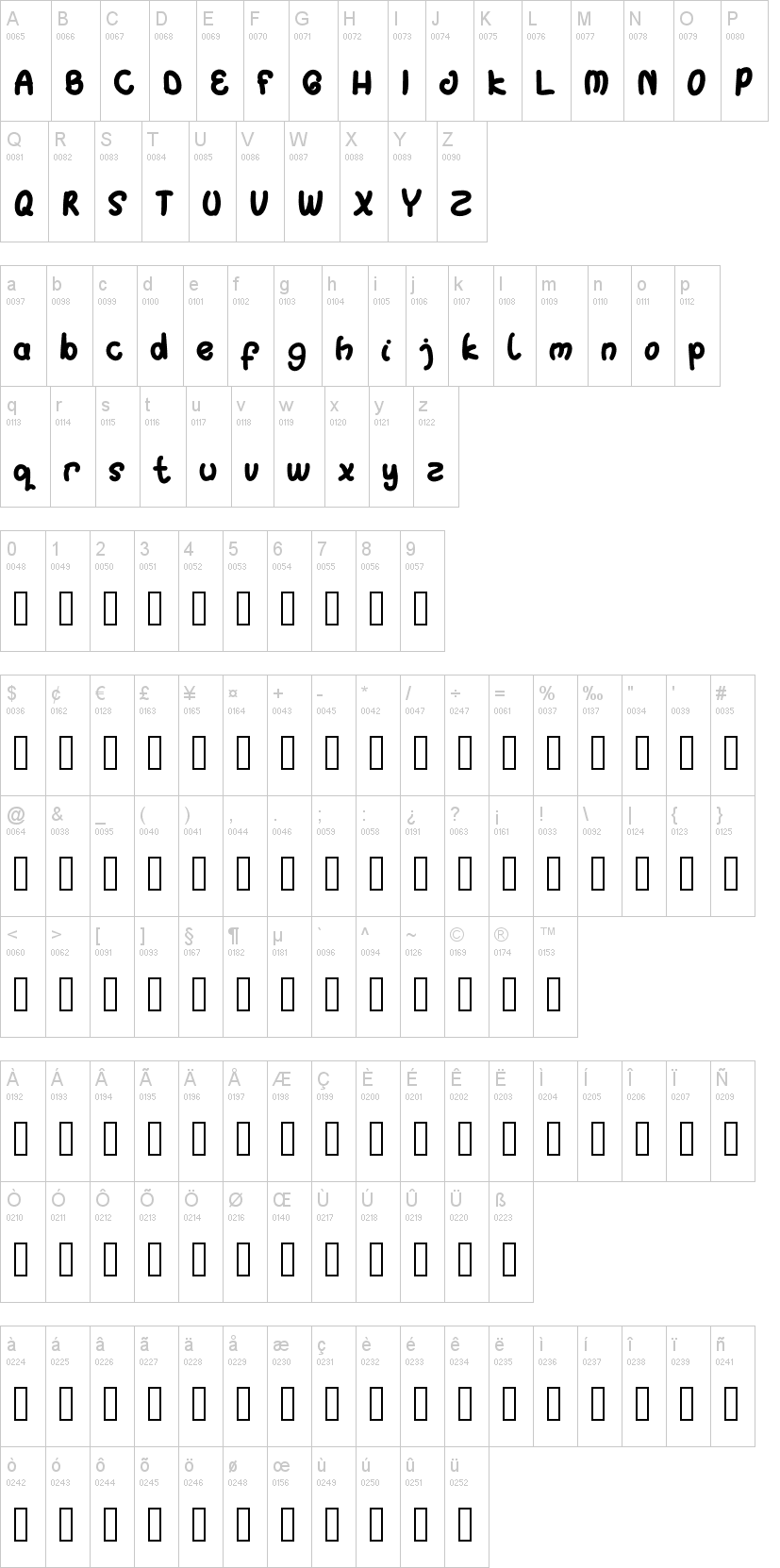
Singo
Singo 是一款非常流行的新型数字字体,它具有极具现代感的外观,具有良好的可读性,可以很好地表达文字的意义。它的元素清晰,简洁,拥有高效的空间利用率,可以有效地表达文字的意义,同时也具有较强的视觉冲击力,可以增强文字的视觉冲击力。它可以应用于多种环境,如网站、平面设计、印刷品等,可以满足不同的设计需求。
Singo是一款非常不错的手写艺术字体,具有很好的视觉感,适合于文化类的宣传设计、商业类品牌的广告和产品包装设计以及个性化文字排版等较多场景。